Gjennom 1800-tallet ble repertoaret av skrift og dekor i norske trykk betydelig utvidet, med nye uttrykksfulle skrifter og ornamenter.
Den første norske skriftprøven, fra Chr. Tønsbergs boktrykkeri i Christiania, utgitt 1849, er et eksempel på det rikere typografiske materiellet som flere norske boktrykkerier etter hvert disponerte.
Dette bredere utvalget av skrift og dekor gjorde det praktisk og nødvendig å utgi en slik skriftprøve – både for kundene og for trykkeriets arbeidere.
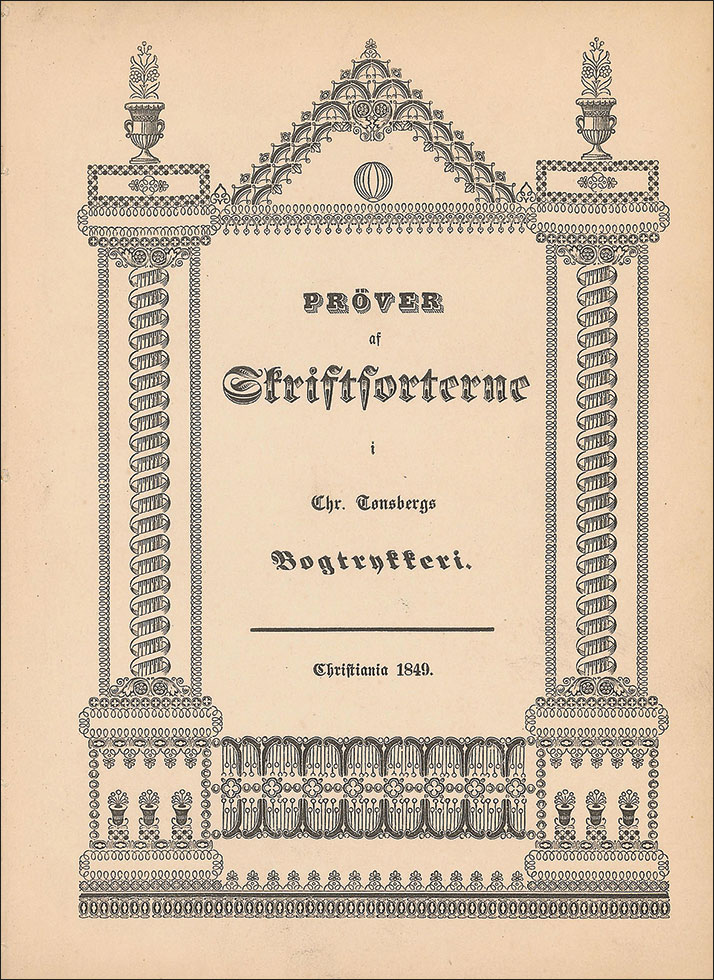
I en artikkel i Norsk bok- og bibliotekhistorisk selskap (NBBS) sin antologi Bokhistorie. Bibliotekhistorie. 2023 har jeg analysert denne skriftprøven, og satt den i sammenheng med Chr. Tønsbergs boktrykkeris historie.
ENGLISH SUMMARY
The first type specimen from a Norwegian printer was published in 1849 by Chr. Tønsberg of Christiania (today’s Oslo). In Bokhistorie. Bibliotekhistorie. 2023 I have written an article which analyses its selection of typefaces.